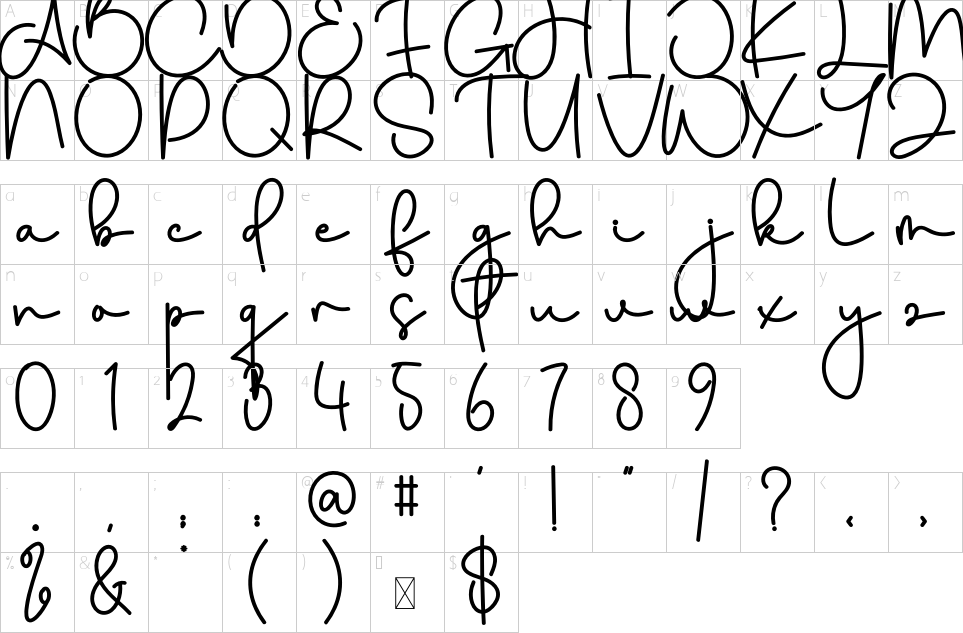
Descubra Gingerbread, uma elegante fonte gráfica grátis para Windows e Mac, perfeitamente adaptada para criar designs de qualidade. Esta font foi criada por scratchones, um designer desconhecido que nos oferece este recurso gratuito de alta qualidade. Com seu design sofisticado e versátil, Gingerbread é uma escolha ideal tanto para designers digitais quanto para entusiastas da gráfica em busca de novos recursos. Além do visual atraente, Gingerbread se destaca por sua facilidade de uso, permitindo que você personalize rapidamente seu design. Seja em um projeto de marketing digital ou no desenvolvimento de interface de usuário, essa font irá ressaltar seus trabalhos. Com apenas dois parágrafos curtos e uma descrição completa, Gingerbread oferece algo especial para qualquer entusiasta da gráfica procurando por uma solução de fonte gratuita. Não perca mais esta oportunidade de adicionar um toque único a seus projetos digitais com Gingerbread.